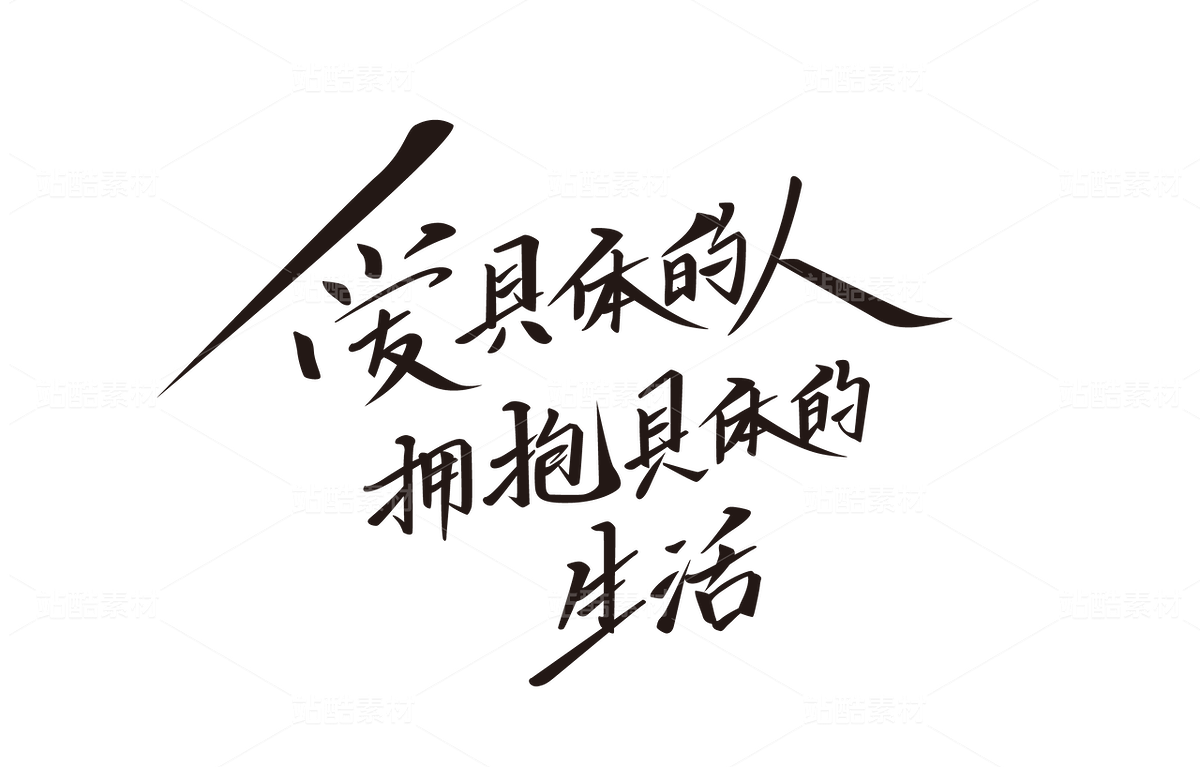
笔画灵动,勾勒生活温度
这组手写字体笔画富有变化,线条流畅自然。“爱” 字起笔轻盈,似心中爱意悄然萌生,撇捺舒展如温暖怀抱;“具”“体” 等字笔画粗细相间,转折处自然流畅,如同生活里的起承转合;“拥” 字笔画紧凑有力,展现出拥抱生活的热情与坚定;“抱” 字的提手旁灵动活泼,与整体风格相呼应,寓意着用双手去拥抱真实。
结构错落,彰显生活节奏
字体结构错落有致,“爱具体的人” 稍显紧凑,传达出情感的专注与真挚;“拥抱具体的生活” 相对开阔,寓意生活的丰富多彩。字与字之间相互呼应,大小、疏密搭配得当,犹如生活既有紧凑忙碌的瞬间,也有舒展惬意的时刻,体现出一种和谐又富有变化的节奏。
风格质朴,传递生活真谛
整体字体风格质朴而真实,没有过多华丽修饰,却精准契合 “爱具体的人,拥抱具体的生活” 这句话所蕴含的哲理。它以一种直白又温暖的方式,提醒人们珍视身边具体的人和日常点滴,将对生活的热爱与感悟,通过手写字体的独特魅力展现得淋漓尽致,给人以触动心灵的力量。
这组手写字体笔画富有变化,线条流畅自然。“爱” 字起笔轻盈,似心中爱意悄然萌生,撇捺舒展如温暖怀抱;“具”“体” 等字笔画粗细相间,转折处自然流畅,如同生活里的起承转合;“拥” 字笔画紧凑有力,展现出拥抱生活的热情与坚定;“抱” 字的提手旁灵动活泼,与整体风格相呼应,寓意着用双手去拥抱真实。
结构错落,彰显生活节奏
字体结构错落有致,“爱具体的人” 稍显紧凑,传达出情感的专注与真挚;“拥抱具体的生活” 相对开阔,寓意生活的丰富多彩。字与字之间相互呼应,大小、疏密搭配得当,犹如生活既有紧凑忙碌的瞬间,也有舒展惬意的时刻,体现出一种和谐又富有变化的节奏。
风格质朴,传递生活真谛
整体字体风格质朴而真实,没有过多华丽修饰,却精准契合 “爱具体的人,拥抱具体的生活” 这句话所蕴含的哲理。它以一种直白又温暖的方式,提醒人们珍视身边具体的人和日常点滴,将对生活的热爱与感悟,通过手写字体的独特魅力展现得淋漓尽致,给人以触动心灵的力量。